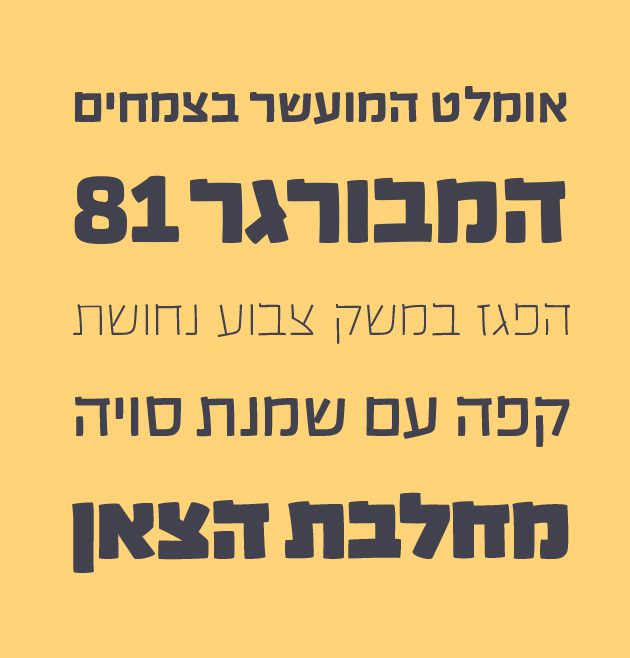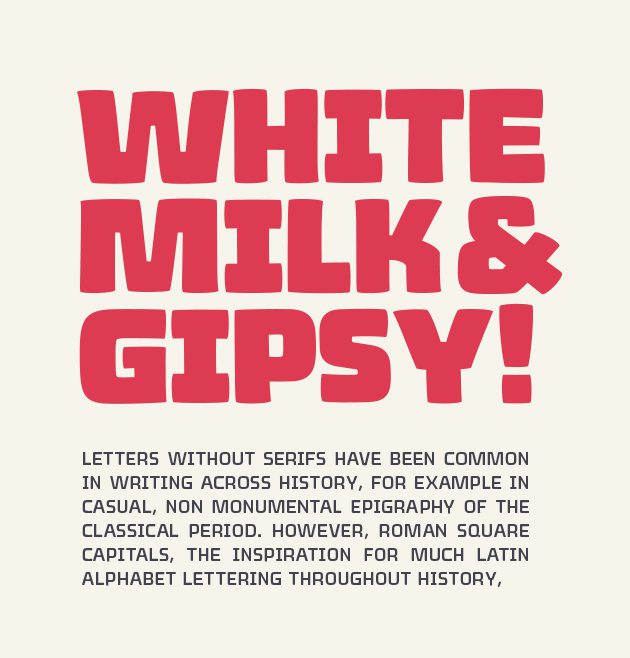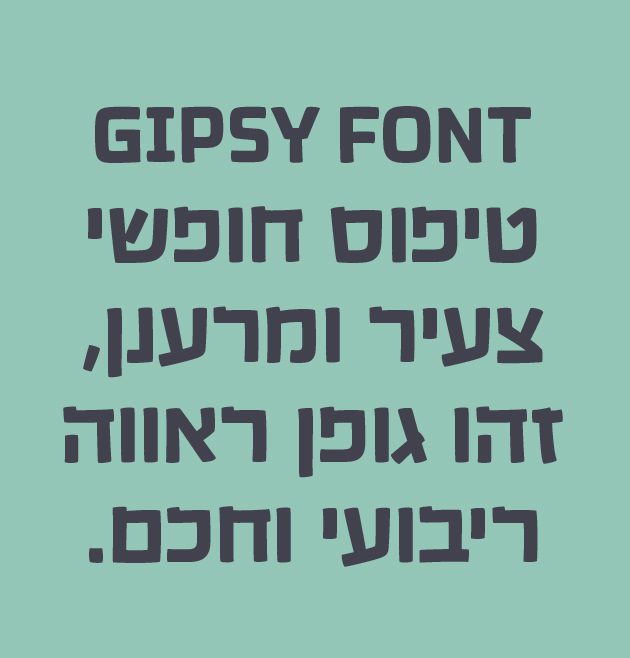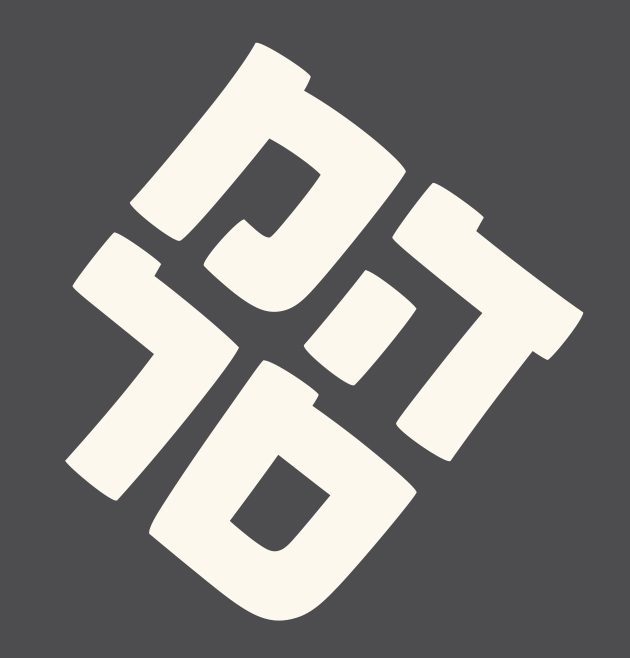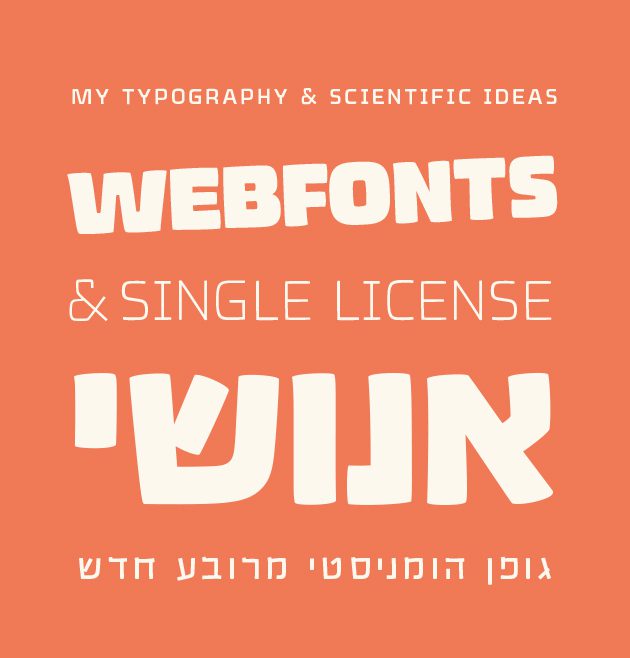
צועני
צועני / Gipsy
• שם הגופן:צועני
• מעצב הגופן:נדב עזרא
• סגנון:כותרות
• מאפיינים: דקיק קל רגיל כבד שחור
• תכונות: אוונגרדי הומניסטי חושני מרובע מתוק נוסטלגי קשיח רוחני שמח
סיפור הגופן:
טיפוס האות צועני, דו-לשוני המאופיין כאות חופשית, הומניסטית, יציבה וכובשת בתנועה קלה ומלאה חינניות. הגופן מיועד לשימוש כאות ראווה ריבועית ומתוחכמת, בעלת קו גרפי מעט מנופח אשר משלב בין סגנון סלאב סריפי לסגנון סנס סריפי. למעשה הייחודיות של האות מתבטא בהעדר של הקווים הסלאב סריפים וחיבור של הסריפים ישירות לגזע האות ובעובי זהה מבחינה אופטית לגזע, כפי שמקובל דווקא בגופנים הסלאב סריפים. טיפוס אות זה למרות היותו גופן ראווה, מצליח בזכות הסריפים להחזיק טקסט רץ ברמת קריאות מפתיעה וטובה. צועני הוא גופן שמח וכיפי לשימוש המשדר טבעיות אלגנטית ונאיבית, בעלת עושר צורני מלא מכל טוב.